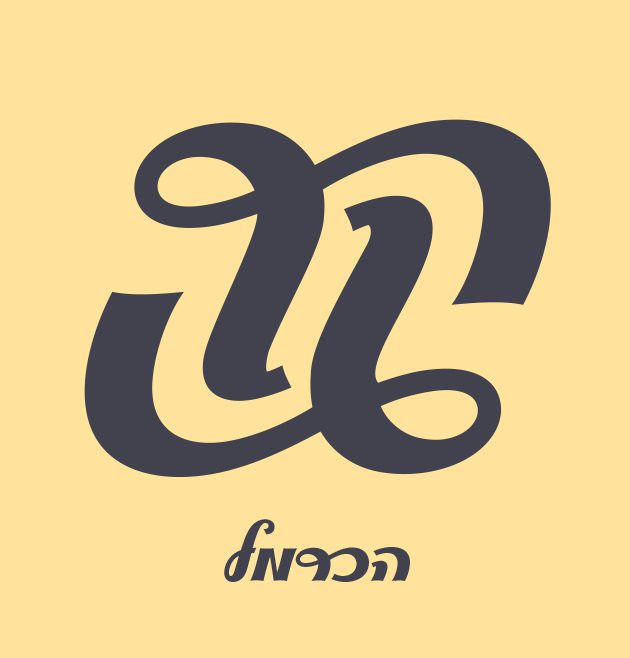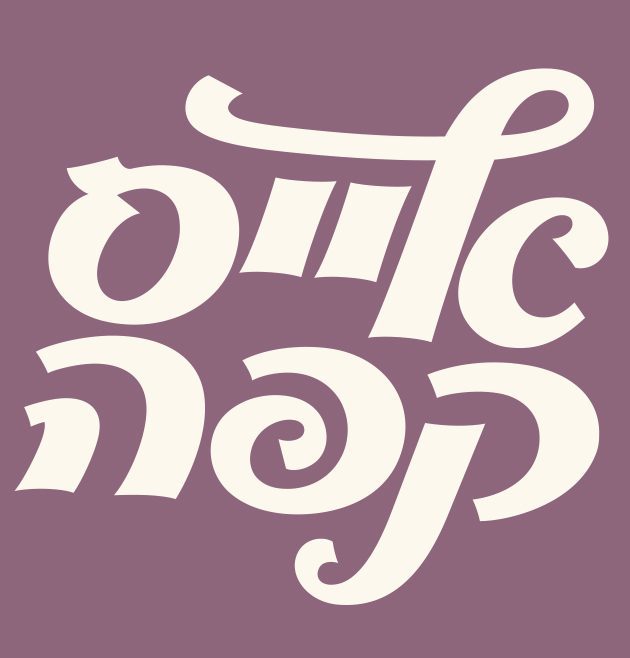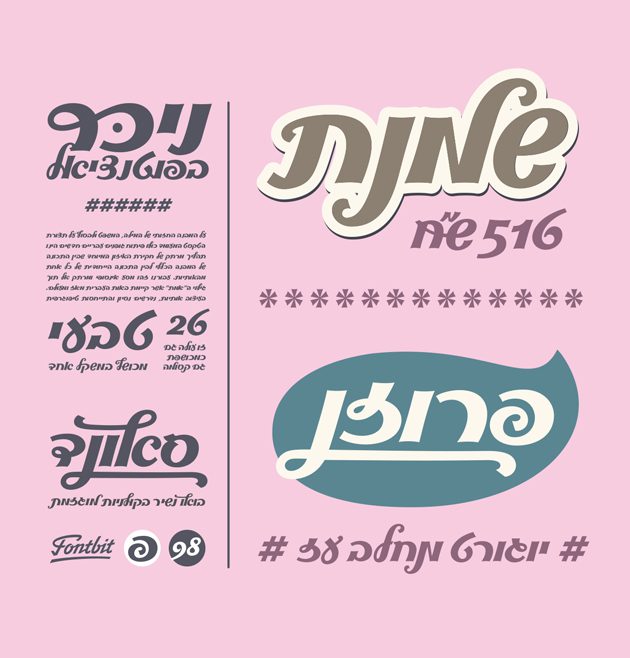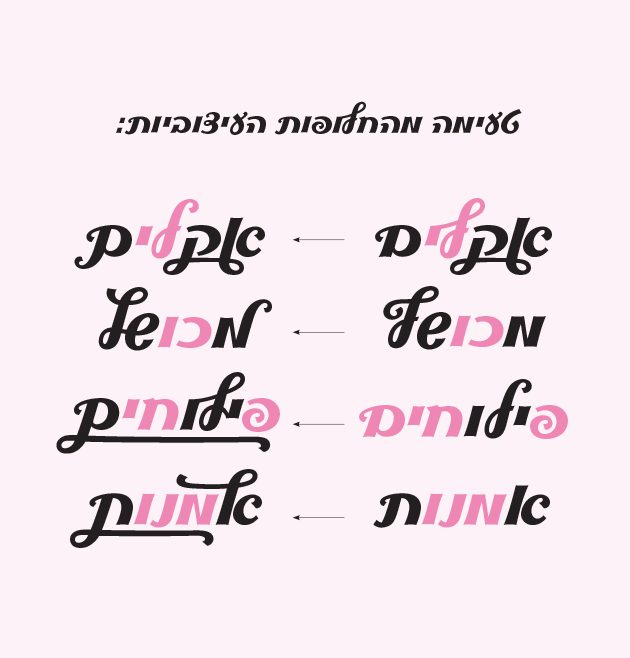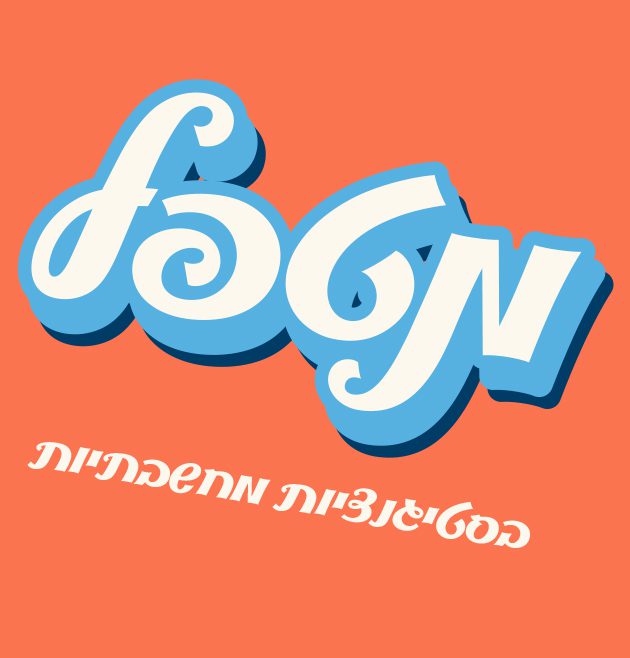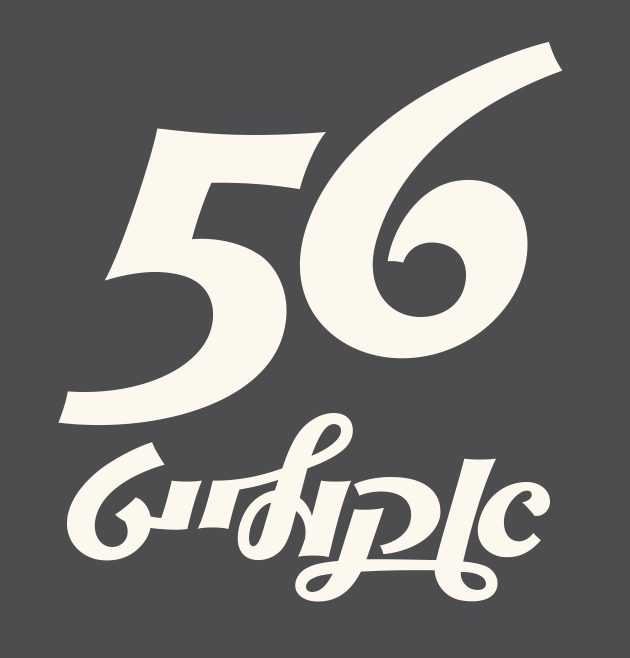
רהוט מכושף
רהוט מכושף / Fb Enchanted Script
סיפור הגופן:
רהוט מכושף הינו גופן רהוט, דינאמי ומועשר בעשרות ליגטורות מדליקות לעיצוב לוגו וכותרות. הגופן קיים במשקל אחד בלבד והוא מאופיין בשמחה, מתיקות ורעננות. הגופן בעל מראה גרפי עם קריצה קליגרפית ומחזיק במתח גדול בין גזעיו לענפיו. מדובר בסוכריה טיפוגרפית כובשת לבבות, מלאה בכריזמה וייחודיות וגם ממש כיפית לשימוש.